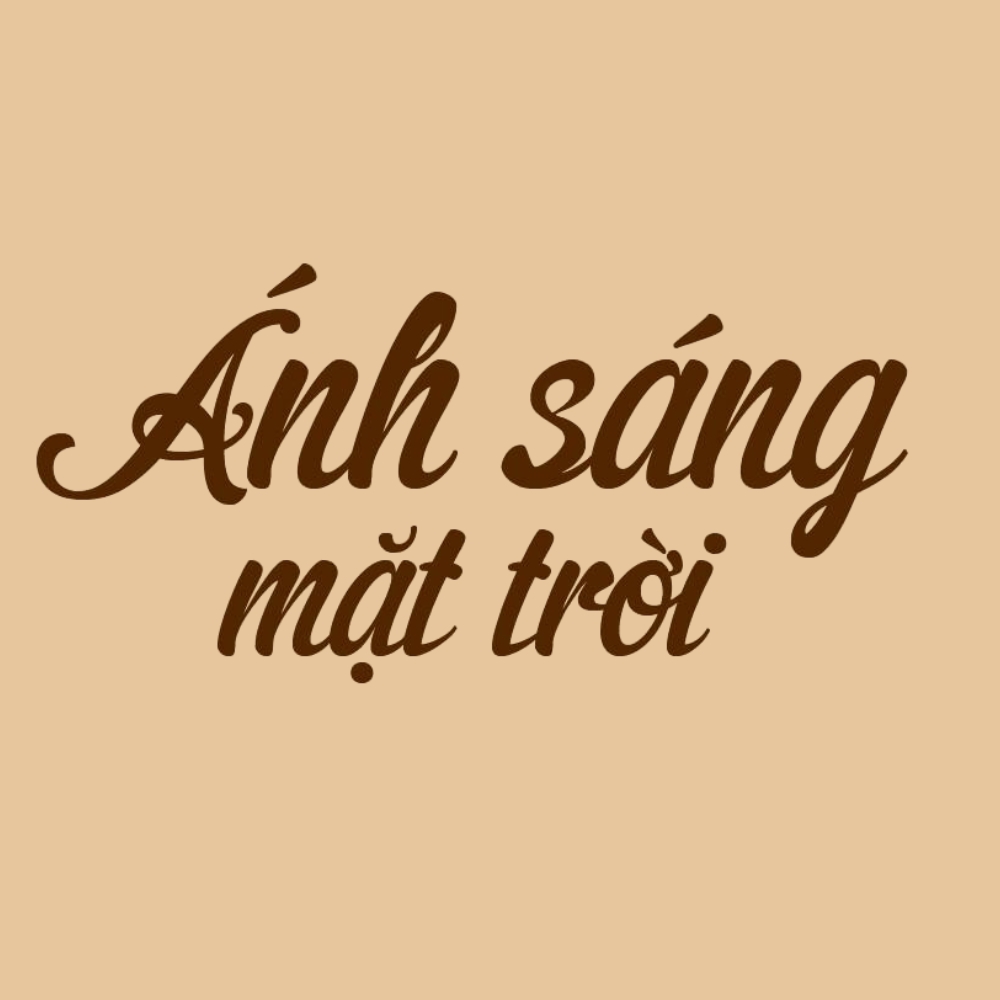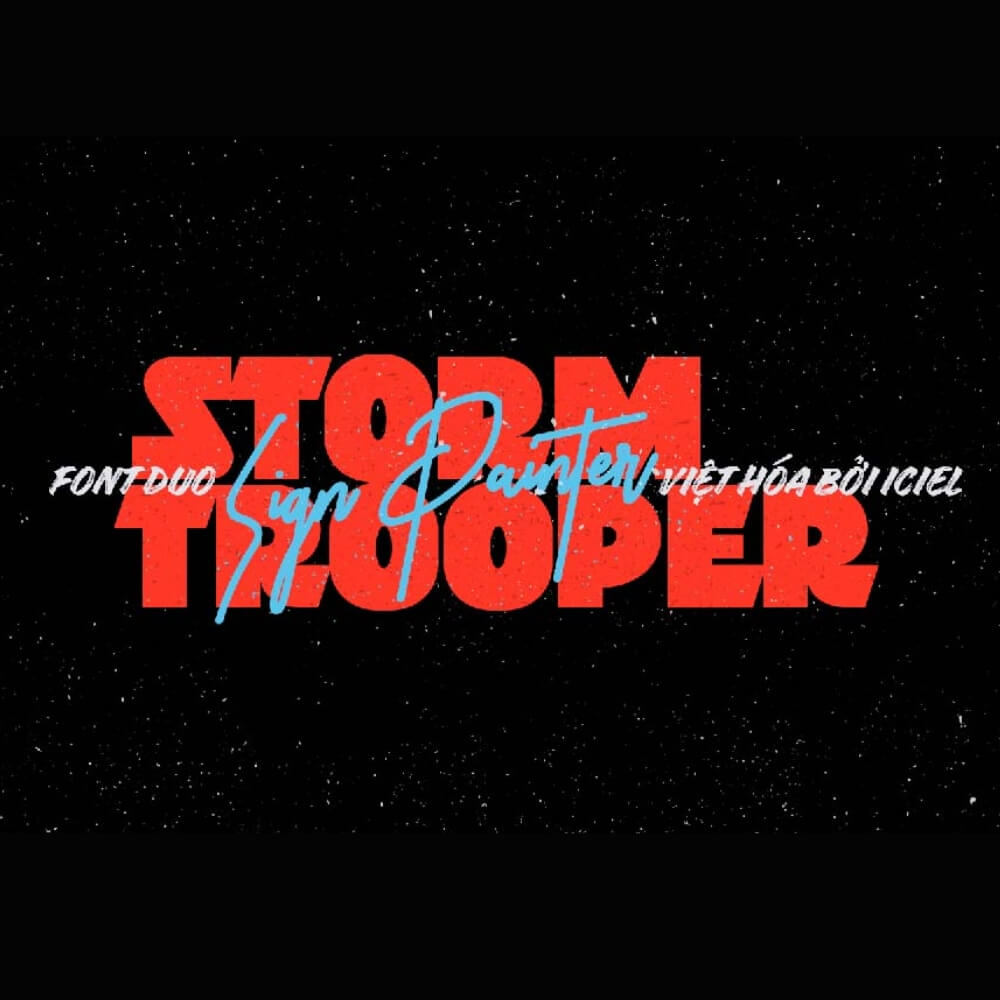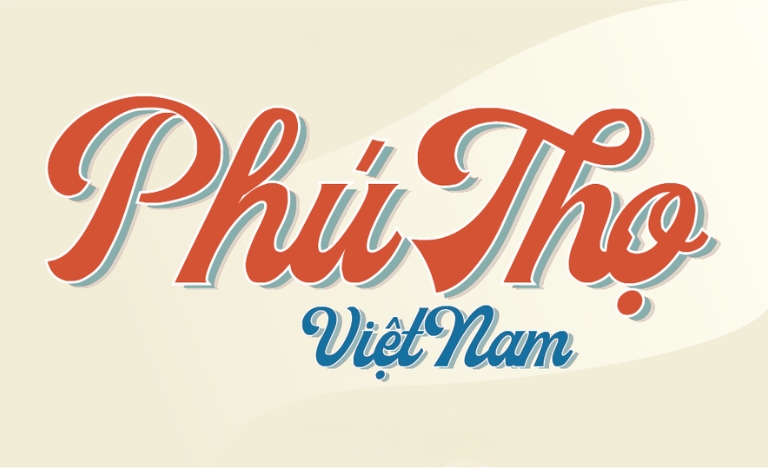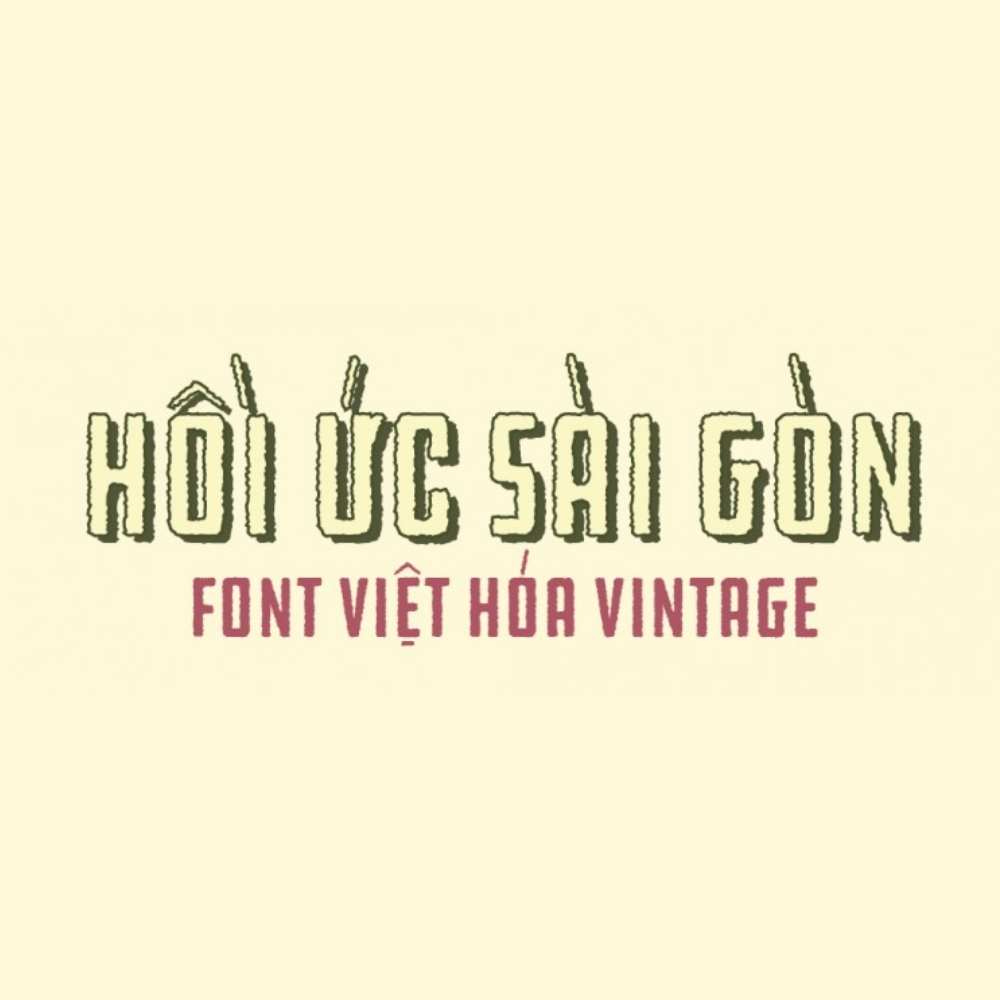
Tải font Retro Việt hóa miễn phí
Font retro việt hóa là font chữ mang phong cách hoài cổ từ thập niên 60s-80s với nét chữ groovy, disco, vintage được sử dụng rộng rãi trong thiết kế bao bì thực phẩm retro, túi giấy cafe vintage và in ấn poster sự kiện. Font chữ vintage việt hóa tạo cảm giác hoài niệm, ấm áp và độc đáo cho thương hiệu.
Ở bài viết này, In Viva giới thiệu bộ sưu tập font chữ retro việt hóa miễn phí với hơn 20 mẫu phong cách đa dạng từ groovy 70s, disco, script vintage đến art deco phù hợp cho thiết kế bao bì và in ấn hoài cổ.
Tham khảo 20+ mẫu font retro việt hóa đẹp
Font retro/vintage mang phong cách hoài cổ đa dạng từ thập niên 1920s đến 1980s. Dưới đây là 20+ mẫu retro font việt hóa phổ biến nhất:Nhóm font retro 70s (groovy, bubble, disco):
• Pacifico (Google Fonts): Font retro surf style, phong cách California 60s-70s, nét viết tay thoải mái.
• Righteous (Google Fonts): Font retro 70s với nét đậm, phong cách groovy, disco.
• Bungee (Google Fonts): Font retro bold, phong cách signage Mỹ thập niên 70s.
• Fredoka One (Google Fonts): Font bubble rounded, vui tươi phong cách 70s.
• Shrikhand (Google Fonts): Font retro Ấn Độ pha trộn Western, độc đáo.
Nhóm font retro script (viết tay cổ điển):
• Lobster (Google Fonts): Font script retro, phong cách biển hiệu cũ 1950s.
• Cookie (Google Fonts): Font script nhẹ nhàng, vintage thanh lịch.
• Sacramento (Google Fonts): Font script liền mạch, cổ điển 40s-50s.
• Allura (Google Fonts): Font script thư pháp vintage, trang nhã.
• Great Vibes (Google Fonts): Font script cursive cổ điển, thanh lịch.
Nhóm font vintage serif (chữ báo cũ, sách cổ):
• Abril Fatface (Google Fonts): Font display serif, phong cách báo chí thế kỷ 19.
• Playfair Display (Google Fonts): Font serif cổ điển, thanh lịch thời Victoria.
• Ultra (Google Fonts): Font serif đậm, phong cách Western vintage.
• Yeseva One (Google Fonts): Font serif Nga cổ điển, trang trọng.
• Cinzel (Google Fonts): Font serif Roman cổ điển, uy nghi.
Nhóm font Art Deco (1920s-1940s):
• Poiret One (Google Fonts): Font geometric Art Deco, thanh lịch 1920s.
• Nixie One (Google Fonts): Font display Art Deco, vintage chic.
• Fascinate (Google Fonts): Font inline Art Deco, Broadway style.
• Monoton (Google Fonts): Font display neon 1920s-1930s.
Vintage Retro font giúp thiết kế trở nên độc đáo và thu hút hơn
Bảng tổng hợp font retro việt hóa free từ Google Fonts:
Tên font
Phong cách retro
Ứng dụng in ấn tốt nhất
Pacifico
Retro surf 60s-70s, California style. Logo cafe vintage, túi giấy beach bar.
Righteous
Groovy 70s, disco, bold. Poster sự kiện music, bao bì thực phẩm retro.
Lobster
Script retro 1950s, biển hiệu cũ. Menu nhà hàng vintage, logo diner.
Abril Fatface
Serif báo chí thế kỷ 19, Victorian. Catalogue vintage, brochure cổ điển.
Poiret One
Art Deco 1920s, geometric elegant. Bao bì mỹ phẩm vintage, thiệp mời gatsby.
Bungee
Retro signage 70s, bold colorful. Poster quảng cáo retro, standee sự kiện.
Sacramento
Script vintage 40s-50s, liền mạch. Thiệp cưới vintage, nhãn sản phẩm handmade.
Ultra
Serif Western vintage, đậm nét. Poster Western, bao bì thực phẩm organic.
Ứng dụng font retro trong thiết kế bao bì
Font retro/vintage mang phong cách hoài niệm được ưa chuộng trong nhiều ngành:
• Tạo cảm giác hoài niệm, ấm áp: Font retro gợi nhớ thời kỳ vàng son 60s-80s, tạo kết nối cảm xúc với thế hệ lớn tuổi và tính độc đáo với thế hệ trẻ.
• Phù hợp thương hiệu heritage, truyền thống: Brand có lịch sử lâu đời hoặc muốn nhấn mạnh giá trị truyền thống, công thức gia truyền.
• Kết hợp tốt với màu vintage: Màu kem, vàng đất, cam gỉ sét, xanh pastel, nâu sepia – tạo bộ màu hoài cổ hài hòa.
• Tạo điểm nhấn độc đáo: Trong thời đại thiết kế minimalist, font retro tạo sự khác biệt, thu hút ánh nhìn.
Font retro xuất hiện rộng rãi trong nhiều sản phẩm in ấn:
• Bao bì thực phẩm retro: bánh kẹo vintage, chocolate cổ điển, cafe rang xay truyền thống.
• Túi giấy cafe phong cách vintage: old school cafe, diner, bistro hoài cổ.
• Menu nhà hàng retro: American diner, Italian trattoria, French bistro cổ điển.
• Nhãn sản phẩm handmade: mứt gia truyền, xà phòng thủ công vintage, nến thơm.
• Poster sự kiện music: rock concert, jazz night, disco party, festival retro.
Font retro phù hợp cho thực phẩm truyền thống, cafe vintage, nhà hàng retro, sản phẩm handmade, thời trang secondhand, sự kiện music, brewery, và mọi thương hiệu muốn tạo cảm giác hoài cổ.